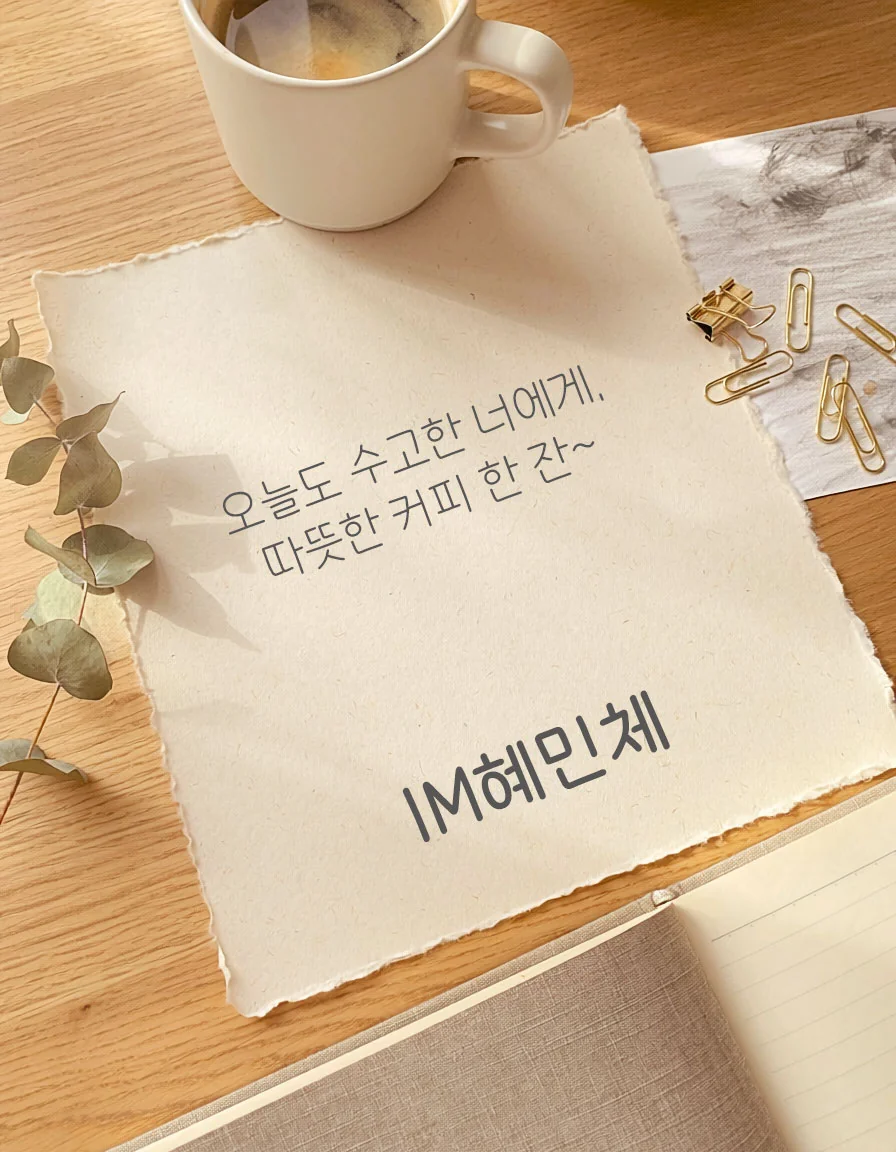
IM혜민체 — DGB대구은행에서 배포하는 무료 폰트입니다. 또박또박한 손글씨에 따뜻하고 친근한 분위기를 담은 개성 있는 서체
DGB대구은행이 2021년 6월에 공개한 서체입니다. **금융권 최초로 직원의 손글씨를 폰트로 만든 사례**로 소개됩니다.
이름을 두고 오해가 잦습니다. 혜민은 스님이 아니라 **대구은행 직원 김혜민 님의 이름**이고, IM은 은행의 디지털 브랜드 이름입니다. 만든 계기도 밝혀져 있습니다. 금융은 딱딱하고 어렵다는 인상을 손글씨 폰트를 통해 바꿔 보고 싶었다는 것입니다. 이 글씨는 먼저 고객상담 챗봇에 적용됐는데, 이용자들의 배포 요청이 이어져 무료 공개로 이어졌습니다.
은행이 붙인 설명은 또박또박 획마다 iM뱅크만의 이야기를 담아낸 폰트라는 한 줄입니다. 파일에서 재어 보면 받침 유무에 따른 높이 차가 거의 없는 네모틀이고 낱자는 정사각형에 가까우며, 획이 가늘어 인상이 단정합니다. 손글씨인데도 글줄이 흐트러지지 않는 이유가 여기 있습니다.
굵기는 Regular와 Bold 두 가지이고 현대 한글 11,172자를 모두 담아, 손글씨 계열치고는 본문에도 쓸 수 있는 구성입니다.